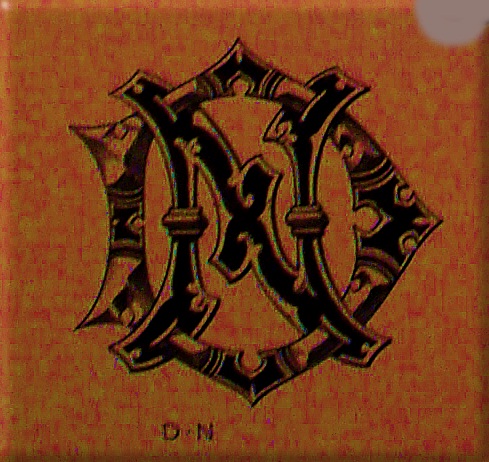
Monograma de todo el alfabeto Demengeot, 1881.
Coloreado, en forma de azulejo |
DEMENGEOT, Ch. "DICTIONNAIRE DE  CHIFFRE-MONOGRAMMES DANS LES STYLESET  RENAISSANCE ET COURONNES NOBILIAIRES UNIVERSELLES."
Paris: Demengeot- Juliot, 1881, 2 Volúmenes.
- Vol. I:  Gran Folio (33x44), Una hoja con la  primera pre-portada con  título y  dedicatoria del  autor manuscrita a:Aglaïus Bouvenne, detrás un monograma, una hoja con un Heliograbado de  Dujardin del retrato de Demengeot,  una hoja  en blanco,  una hoja repitiendo la  1ª portada igual que  el primer  folio,  una hoja con la portada a dos tintas, rojo y negro,  tres hojas  numeradas en romanos,  98 páginas de la primera parte, 116 páginas de la segunda  parte, 1 hoja con  la justificación de la tirada, una hoja en blanco.
- Vol. II: Gran  Folio (33x 44), Atlas de láminas, la portada con el famoso Monograma de todo el  alfabeto grabado por el autor y colección de 33 láminas con diferentes  monogramas y coronas heráldicas.
Tirada solo de 200  ejemplares en gran folio y papel  superior.
Sin duda es un libro en  mayúsculas y el trabajo y diseño de los monogramas lo sitúan en la cumbre de  esta especialidad.
En esta entrada pondré los monogramas y nombres que contienen las láminas 5, 6, 7 y 8 de este libro, esto incluye las letras C y D con sus combinaciones con las letras letras del alfabeto, también incluye algunos nombre propios y algunas coronas.
LETRA C
| Lámina nº 5 Demengeot-1881 |
| Lámina nº6 Demengeot-1881 |
| C-C |
| CATHERINE |
| C-D |
| C-E |
| C-F |
| C-G |
| C-H |
| C-I |
| C-J |
| C-K |
| C-L |
| C-M |
| C-N |
Monograma de Charles Austria
| C-O |
| C-P |
| C-Q |
| C-R |
| C-S |
| C-T |
| C-U |
| C-V |
| C-W |
| Corona de Aquitania |
| Corona de Carlos el Calvo |
| Corona de Carlomagno |
| Corona de Luis IX |
| C-X |
C-Y
| C-Z |